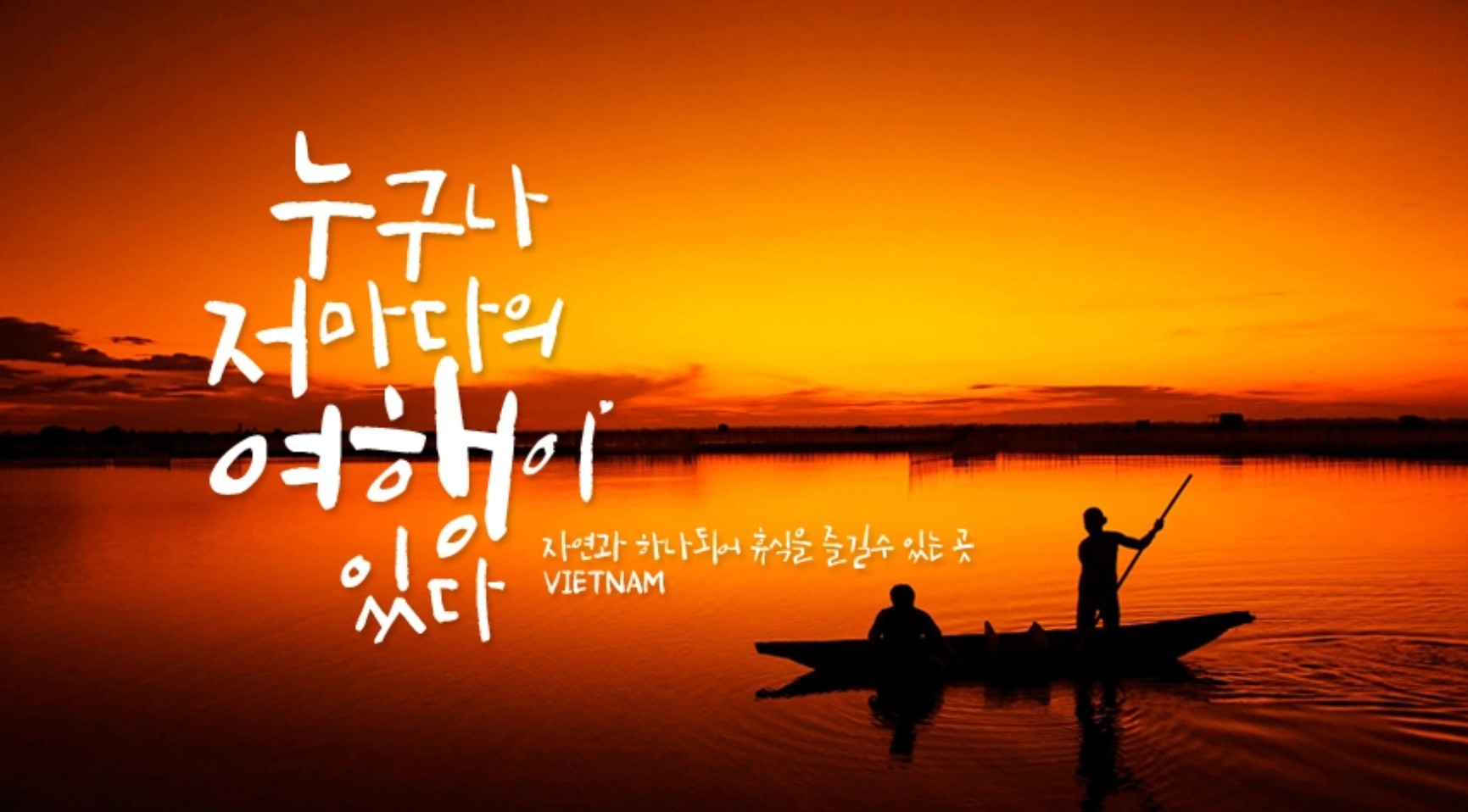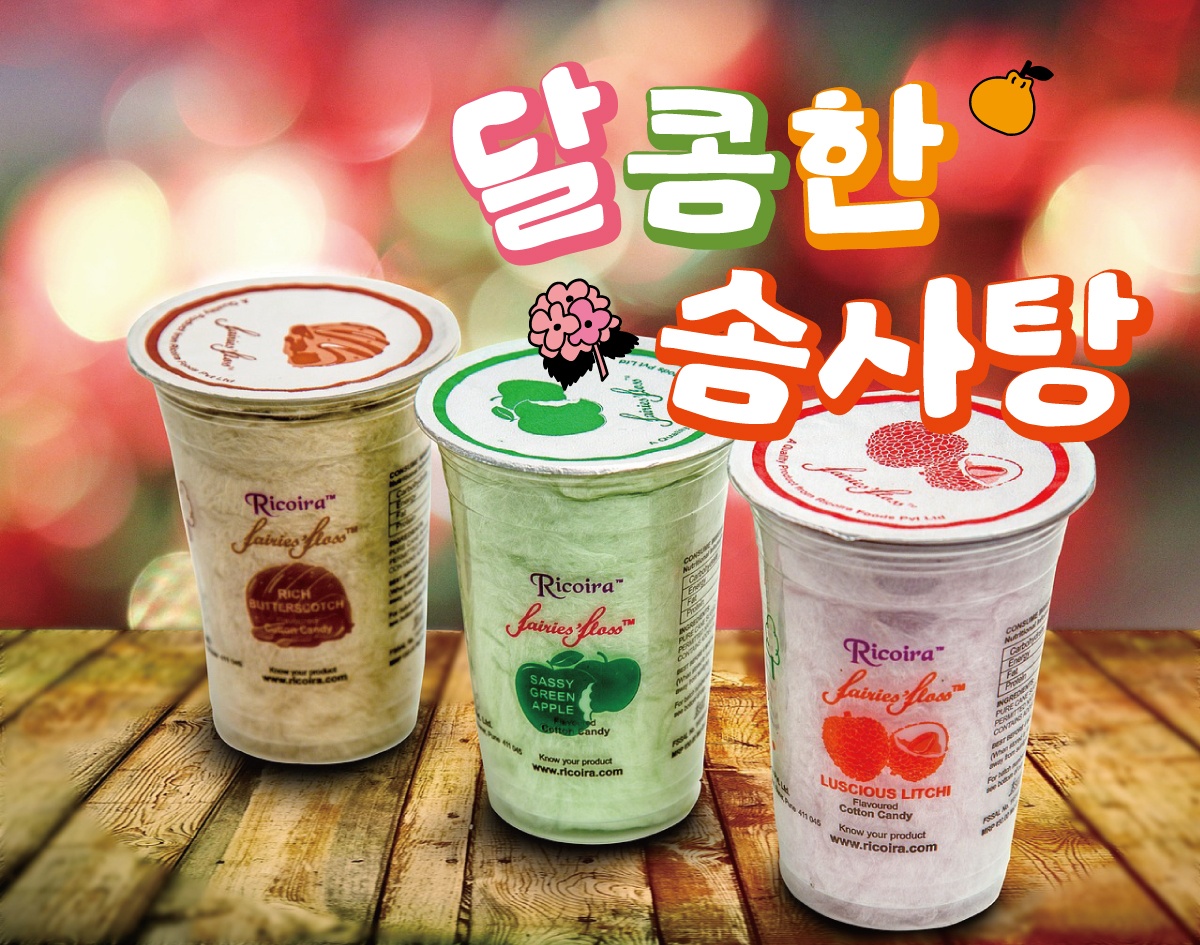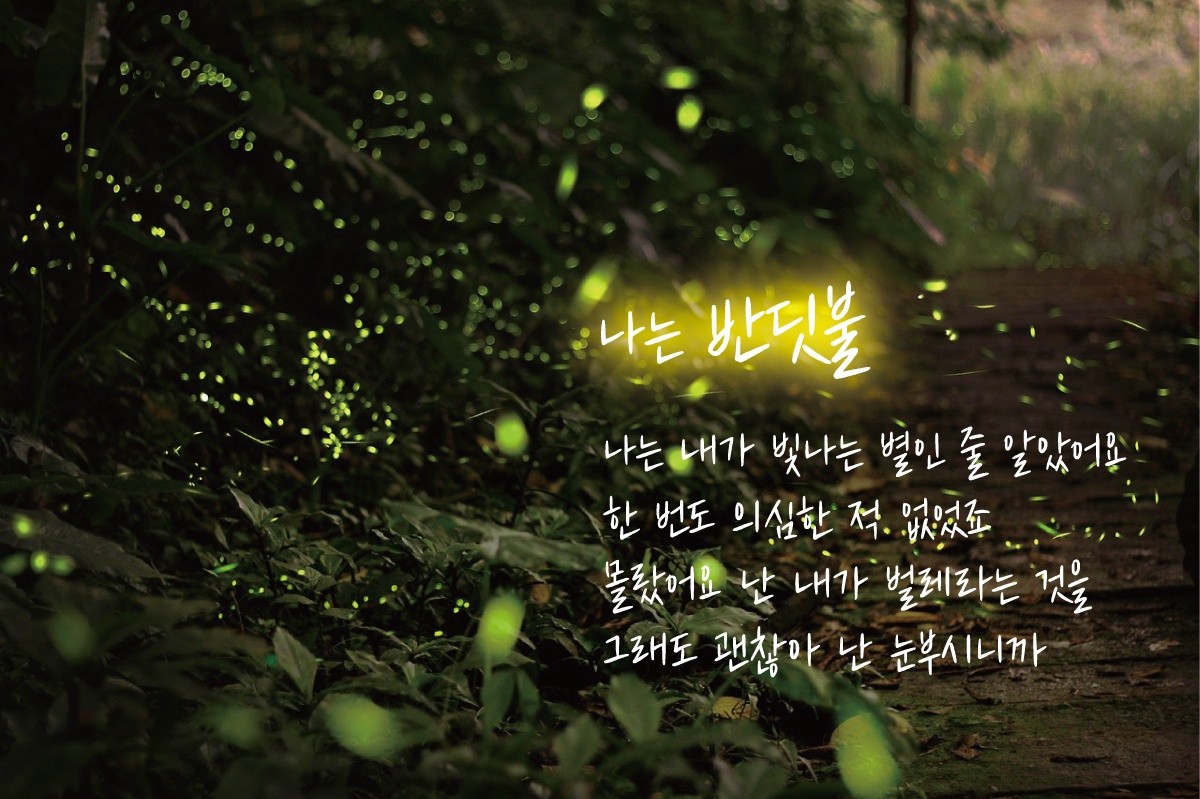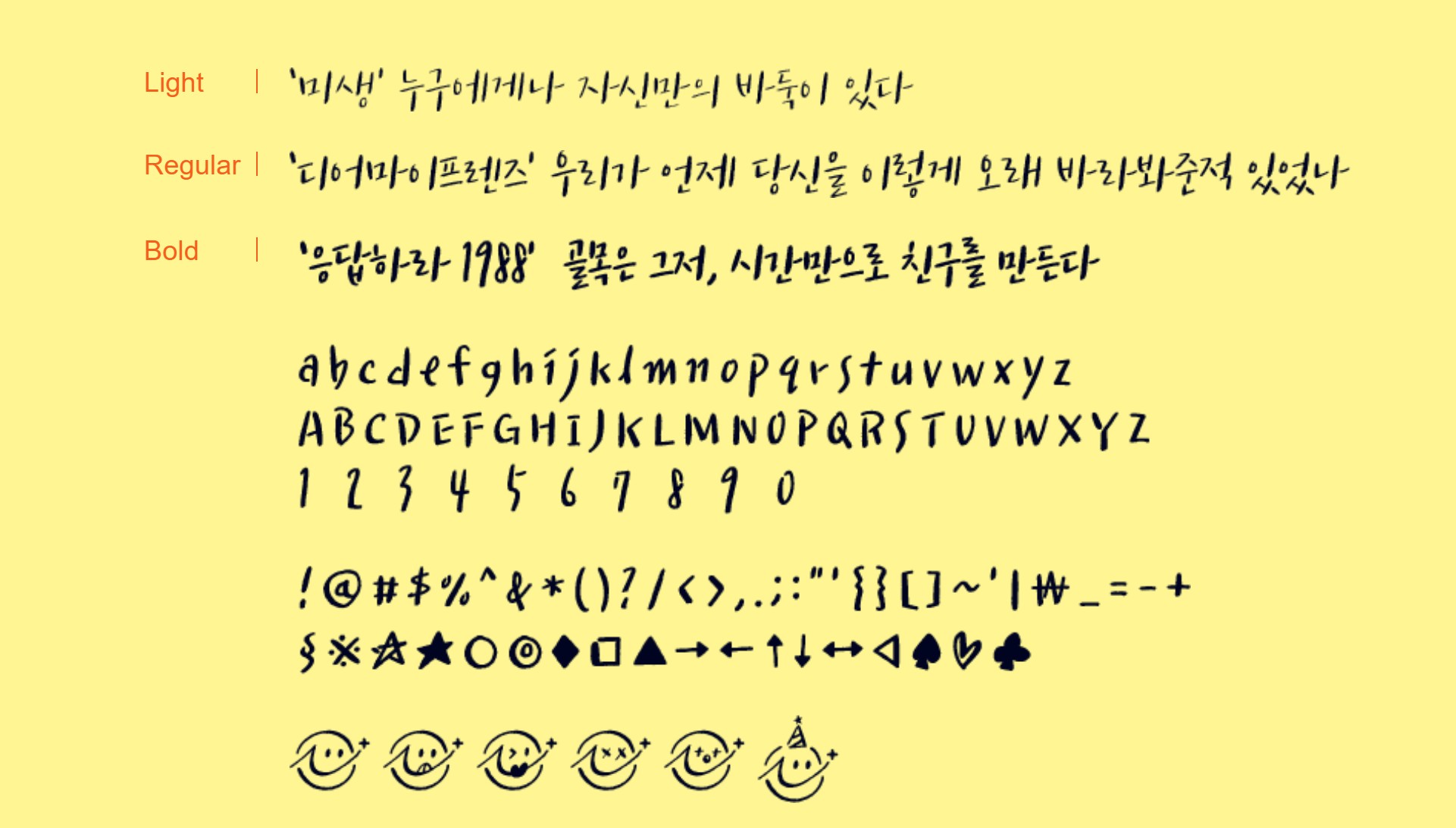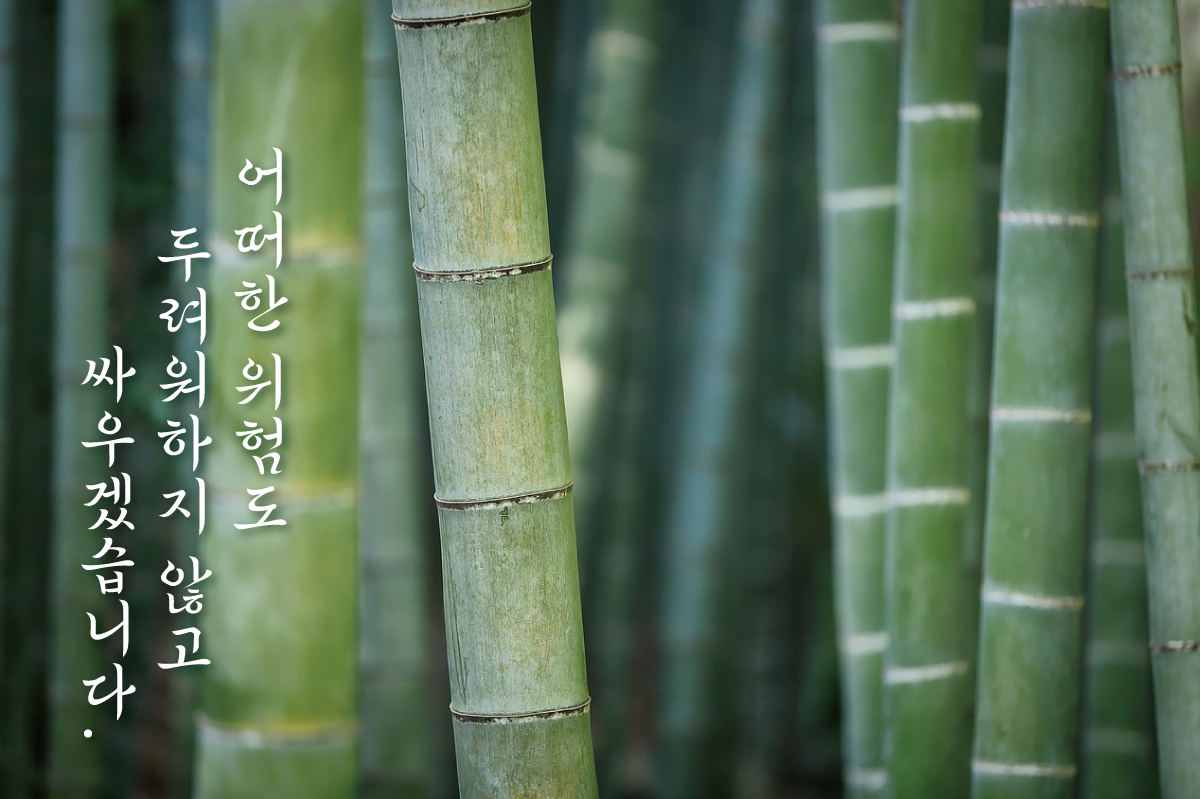
감성을 자극하는 손글씨 폰트를 찾고 계신가요? 디자인에 깊이를 더하고, 메시지에 감정을 입히는 데 딱 좋은 캘리그라피 서체들을 모았습니다. 지금 소개할 20종의 서체는 무료로 사용할 수 있을 뿐만 아니라, 각기 다른 배경과 감성을 품고 있어요. 이 중 하나쯤은 당신의 콘텐츠를 완성해 줄 운명일지도 모릅니다.
캘리그라피 손글씨 폰트 20종
캘리그라피 신라문화체
신라문화체는 고대 경주의 신라 미학을 서체로 담아낸 서체입니다. 곡선미가 강조되어 우아하고 단정한 인상을 주며, 역사 콘텐츠나 관광 홍보물에 자주 활용됩니다.
캘리그라피 정선아리랑체
강원도 정선의 전통 민요 '정선아리랑'에서 영감을 받은 서체로, 흐르는 듯한 유연한 획이 특징입니다. 전통과 현대가 어우러지는 프로젝트에 잘 어울립니다.
캘리그라피 제주돌담체
제주도의 정취가 서체 속에 담긴 제주돌담체는 투박하면서도 자연스러운 느낌을 줍니다. 돌담의 울퉁불퉁한 형태를 닮은 획이 특징이며, 제주 특산품 포장지나 관광 리플릿에 제격입니다.
캘리그라피 손글씨 정묵바위체
강인함과 굳건함을 상징하는 정묵바위체는 바위에 새긴 암각문에서 영감을 받아 제작된 서체입니다. 획이 두껍고 날카로워 무게감 있는 메시지를 전달할 때 효과적입니다.
캘리그라피 나눔손글씨펜체
나눔손글씨 펜은 국민 서체로 불릴 만큼 친숙한 손글씨 폰트입니다. 부드럽고 일상적인 필체가 특징으로, 일기, 블로그, SNS 카드뉴스 등 다양한 용도에 활용도가 높습니다.
카페24 빛나는 별체
별처럼 반짝이는 감성을 표현한 카페 24 빛나는별 폰트는, 얇고 부드러운 획이 인상적입니다. 감성적인 무드의 브랜딩, 인스타 피드 디자인에 특히 인기가 많습니다.
추사 사랑체
추사 김정희의 예술적 필체에서 영감을 얻은 추사 사랑체는, 전통 서예의 품격과 현대적인 해석을 동시에 담고 있습니다. 전통 전시회, 문화재 관련 안내문에 적합합니다.
캘리그라피 손글씨 만세체
만세운동을 기념하기 위해 제작된 만세체는 자유롭고 강렬한 획이 인상적입니다. 포스터, 캠페인 문구 등에 사용하면 독립정신의 감성을 효과적으로 표현할 수 있습니다.
캘리그라피 상상토끼 꽃길체
화사하고 감성적인 분위기를 자아내는 꽃길 서체는, 마치 꽃잎이 흩날리듯 자유로운 획의 움직임이 돋보입니다. 결혼식 청첩장, 로맨틱한 이벤트 디자인에 제격입니다.
캘리그라피 수성혜정체
따뜻하고 부드러운 여성스러움이 느껴지는 수성혜정체는, 적당한 자간과 깔끔한 획 덕분에 가독성도 뛰어납니다. 포스터, 상품 패키징에 감성을 더할 수 있는 서체입니다. (출처표기)
캘리그라피 행복고흥체
고흥군이 개발한 행복고흥 서체는 이름처럼 밝고 따뜻한 인상을 줍니다. 다소 귀여운 느낌의 곡선이 강조되어 지역 특산물 포장이나 친환경 브랜드에 잘 어울립니다.
캘리그라피 김정철손글씨체
작가 김정철의 실제 손글씨를 바탕으로 제작된 이 서체는, 진솔하고 인간적인 감성이 담겨 있습니다. 감성 글귀, 명언 이미지 제작 시 생동감을 부여합니다.
캘리그라피 포천막걸리체
막걸리의 구수함과 정겨움을 표현한 이 서체는 투박하면서도 따뜻한 분위기를 자아냅니다. 전통주 라벨, 지역 특산물 브랜딩에 탁월한 선택입니다.
캘리그라피 솔뫼김대건체
한국 최초의 천주교 사제 김대건 신부의 숭고한 정신을 담아 제작된 서체입니다. 경건하고 고요한 분위기를 전달하는 데 적합하며, 종교 간행물이나 기념 콘텐츠에 자주 활용됩니다.
캘리그라피 글씨체 무료 폰트
노회찬체
고 노회찬 의원의 손글씨를 바탕으로 만들어진 서체입니다. 단정하고 명료하면서도 인간적인 감성이 느껴지는 이 글꼴은 정의, 사회운동 관련 콘텐츠에 자주 등장합니다.
캘리그라피 손글씨 독립체
독립체는 광복절, 3.1절 등 독립운동 기념일에 어울리는 대표 서체입니다. 힘차고 굵은 획은 당시의 결기와 열정을 담고 있으며, 태극기의 상징성과도 잘 어울립니다.
캘리그라피 즐거운이야기체
아이의 손글씨처럼 따뜻하고 순수한 즐거운이야기체는 긍정적인 느낌을 주는 서체입니다. 유아 교육 자료, 동화책, 초대장 등에서 자주 사용됩니다.
캘리그라피 글씨체 무료 폰트
캘리그라피 영양군음식디미방체
조선시대 대표 요리책인 음식디미방의 고전적 서체를 현대적으로 복원한 글꼴입니다. 전통음식 콘텐츠, 요리책, 문화재 관련 간행물에 유용합니다.
울산중구전용서체
울산 중구청에서 지역의 정체성과 현대 감각을 반영하여 제작한 전용서체입니다. 도시적인 느낌과 감성적인 요소가 조화롭게 어우러져 공공 콘텐츠에 적합합니다.
캘리그라피 정선아리랑혼체
정선아리랑체의 감성을 더욱 강화한 혼체는, '혼'이라는 단어처럼 깊은 감정과 역사적 의미가 담겨 있습니다. 문화공연 포스터나 감성 깊은 전시 콘텐츠에 잘 어울립니다.
Q4. 감성 글귀나 카드뉴스에 어울리는 서체는?
나눔 손글씨펜, 꽃길, 카페 24 빛나는 별, 즐거운 이야기체 등을 추천합니다.
Q5. 역사나 전통 관련 콘텐츠에 어울리는 서체는?
추사 사랑체, 정묵바위체, 정선아리랑혼체, 영양군 음식디미방체가 적합합니다.